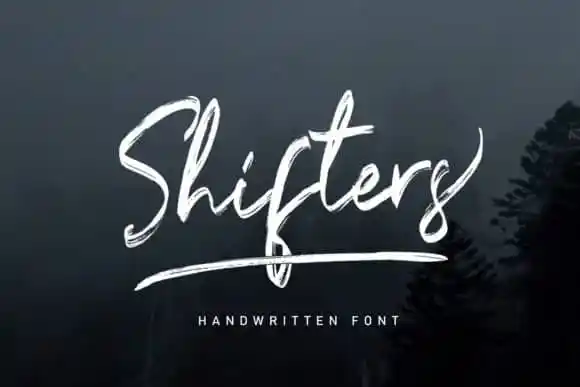
Shifters Brush Font – Fonte Grátis
Shifters Brush Font
A fonte Shifters Brush é perfeita para quem busca uma adição sofisticada a qualquer projeto DIY. Seu design exala elegância, luxo e modernidade, criando um texto impecável e atual. Criada pela designer Arendxstudio, a fonte resulta de uma combinação incrivelmente delicada entre uma caneta-pen e um grafiteiro, tornando-a irresistivelmente encantadora e autêntica. Seja para uma decoração caseira ou até mesmo para adicionar aquela pitada única em sua próxima arte digital, a fonte Shifters Brush é o complemento perfeito para transformar qualquer projeto em algo verdadeiramente especial.